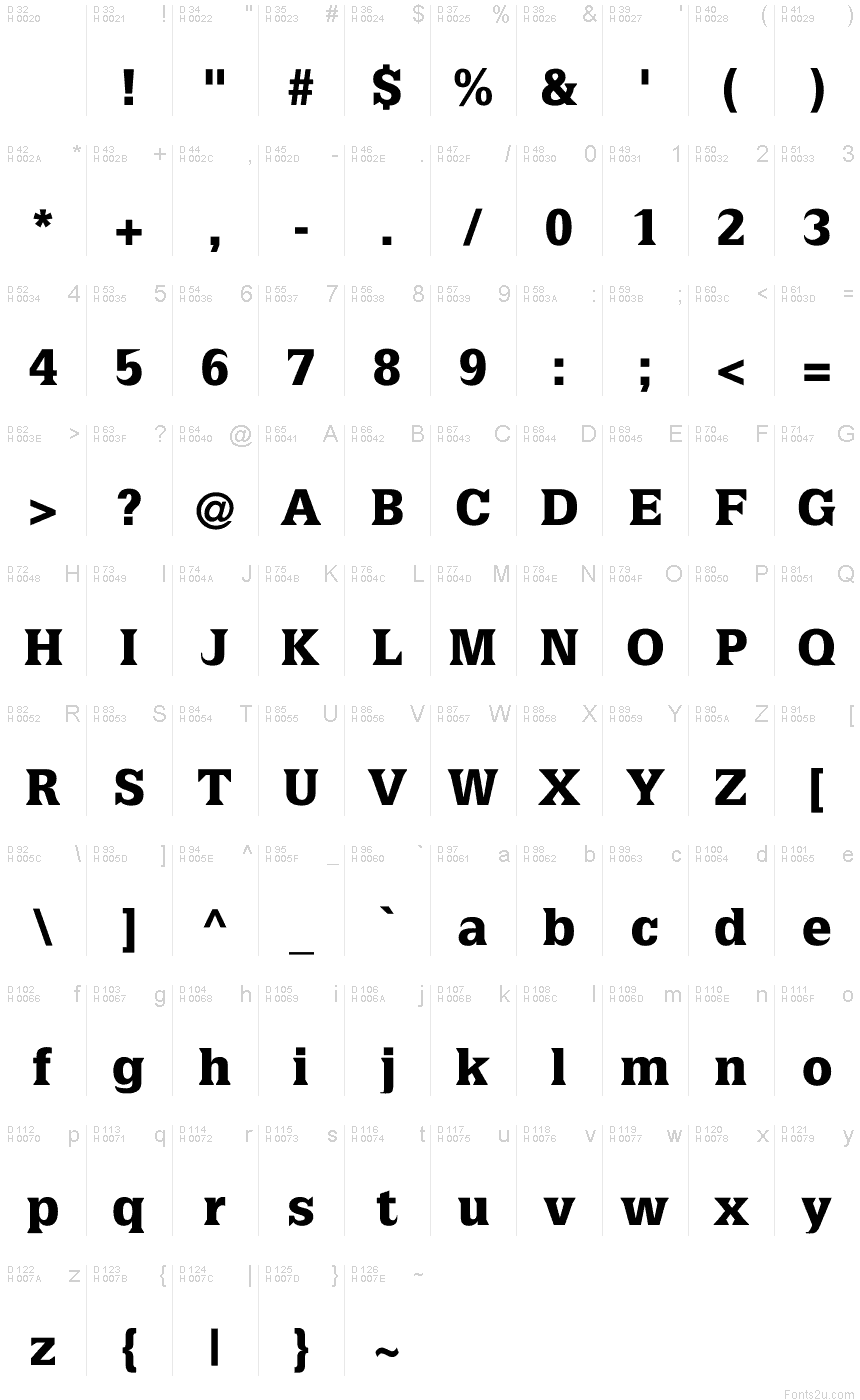
LatiniaBlack
Latinia Black autorstwa M. Klein to darmowy krój szeryfowy o rzymskim charakterze, stworzony z myślą o plakatach. Litery sprawiają wrażenie wykutych i ciężkich, z szerokimi szeryfami klinowymi, głębokimi łukami i zwartym rytmem, który nadaje nawet prostym słowom dramatyczny, staroświecki wyraz.
Sprawdzi się na okładkach książek, etykietach win, w brandingu restauracji, na plakatach wydarzeń i w planszach tytułowych, gdzie ten darmowy font wniesie szczyptę łacińskiej elegancji, nie stając się przy tym przesadnie zdobnym. Wykorzystaj go również do krótkich nagłówków, inicjałów czy monogramów; gęsta plama koloru i ciosane szeryfy nadają krótkim liniom tekstu mocny, emblematyczny charakter.